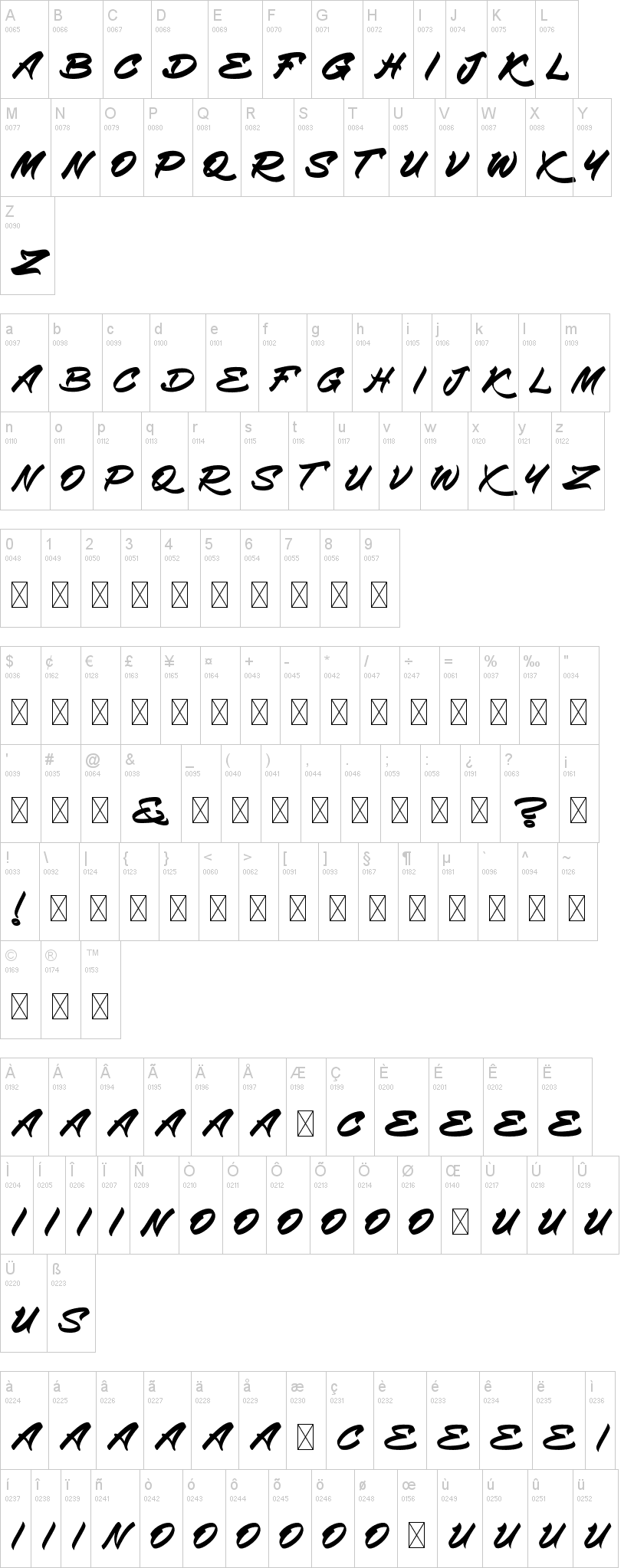
? Empire Samgor 字体是一款由英国设计师Sam Gorst设计的英文字体,它拥有独特的古典风格,采用了细节丰富的结构以及英文字母的传统形式。该字体有一种浓厚的古典气息,是一款非常适合用于报纸、杂志、书籍、海报、品牌标识等的字体。内容介绍
Empire Samgor是一款非常不错的手写艺术字体,具有很好的视觉感,适合于文化类的宣传设计、商业类品牌的广告和产品包装设计以及个性化文字排版等较多场景。